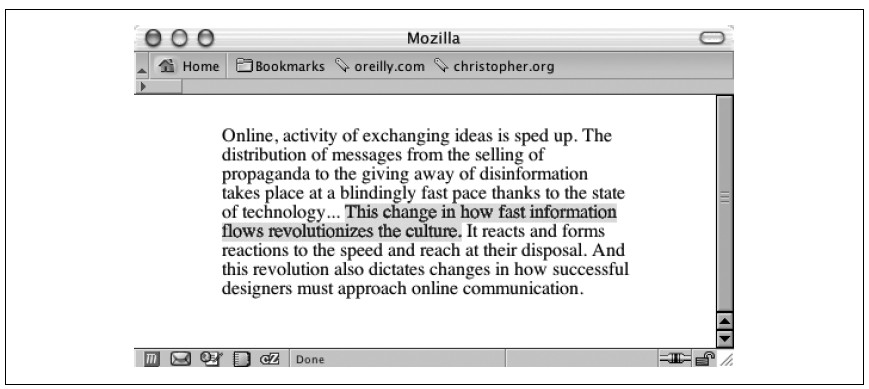
Textteile hervorheben
Problem
Bestimmte Textteile eines Absatzes sollen hervorgehoben werden, wie in der folgenden Abbildung gezeigt.
Abbildung: Hervorgehobener Text.
Lösung
Markieren Sie die Teile Ihres Textes, die hervorgehoben werden sollen, mit dem Element strong:
<p>The distribution of messages from the selling of propaganda to the giving away of disinformation takes place at a blindingly fast pace thanks to the state of technology … <strong>This change in how fast information flows revolutionizes the culture.</strong> ...</p>
Nun definieren Sie die entsprechenden CSS-Regeln, um den Text hervorzuheben:
strong {
font-weight: normal;
background-color: yellow;
}
Diskussion
Anstelle des strong-Elements in dieser Lösung hätten Sie auch das Element em verwenden können, um den hervorzuhebenden Text zu markieren. Laut der HTML 4.01-Spezifikation soll em für die Markierung von hervorgehobenem Text benutzt werden, während strong "stärker hervorgehobenen Text" bezeichnen soll.
Nachdem Sie den Text markiert haben, können Sie mit der Eigenschaft background-color festlegen, welche Farbe für die Hervorhebung benutzt werden soll. Da manche Browser als strong markierten Text fettgedruckt darstellen, sollten Sie zusätzlich die Eigenschaft font-weight (Schriftgewichtung) auf den Wert normal setzen. Bei der Verwendung von em müssen Sie dagegen die Eigenschaft font-style auf normal setzen, um zu verhindern, dass manche Browser derartig markierte Teile kursiv darstellen, wie im folgenden Codebeispiel zu sehen ist:
em {
font-style: normal;
background-color: #ff00ff;
}